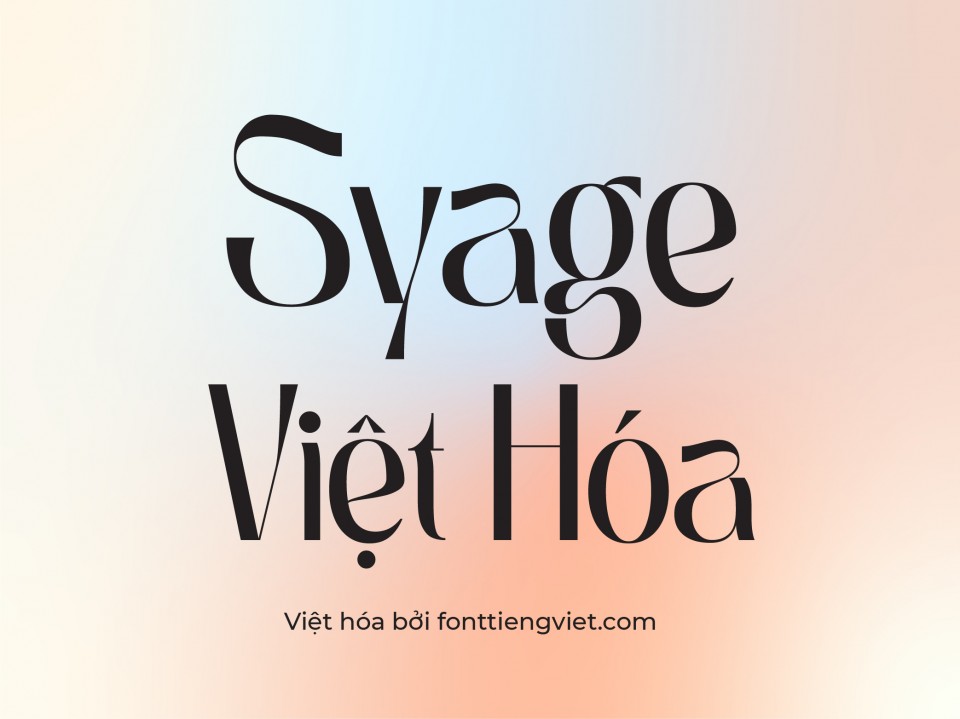
Font việt hóa 1FTV Syage
Giới thiệu về Font việt hóa 1FTV Syage
Trong thế giới thiết kế đồ họa hiện đại, việc lựa chọn một bộ Font Miễn Phí chất lượng luôn là ưu tiên hàng đầu của các designer. Font việt hóa 1FTV Syage nổi lên như một hiện tượng nhờ sự kết hợp hoàn hảo giữa nét cổ điển và hơi thở đương đại. Đây là bộ phông chữ Serif mang phong cách thanh lịch, giúp mọi ấn phẩm từ bìa sách đến biểu trưng thương hiệu trở nên sang trọng hơn. Việc sở hữu bản việt hóa chuẩn giúp người dùng không còn lo lắng về lỗi gõ dấu tiếng Việt, đảm bảo tính thẩm mỹ tuyệt đối cho mọi dự án sáng tạo tại Việt Nam.
Đặc điểm nổi bật của Font việt hóa 1FTV Syage
Nét vẽ tinh tế và độ tương phản cao
Điểm thu hút nhất của Font việt hóa 1FTV Syage chính là những đường nét thanh mảnh đan xen với những nét đậm dứt khoát. Cấu trúc chữ cái được chăm chút tỉ mỉ, tạo nên sự cân đối thị giác rất tốt. Điều này giúp bộ font không chỉ đẹp khi dùng làm tiêu đề mà còn cực kỳ dễ đọc ở các đoạn văn bản ngắn. Sự linh hoạt này giúp các em học sinh và thầy cô dễ dàng ứng dụng vào việc làm slide bài giảng hoặc thiết kế báo tường sinh động.
Khả năng ứng dụng đa dạng
Dòng phông chữ này cực kỳ phù hợp cho các thiết kế mang tính thời trang, tạp chí hoặc poster sự kiện cao cấp. Nhờ bộ ký tự tiếng Việt được hiệu chỉnh kỹ lưỡng, bạn có thể tự do sáng tạo mà không sợ bị lệch tông hay hỏng bố cục. Độ tương thích cao trên các phần mềm như Photoshop, AI hay Canva cũng là một điểm cộng lớn khiến nó trở thành lựa chọn hàng đầu cho cộng đồng thiết kế Việt.
Kết luận về bộ phông chữ 1FTV Syage